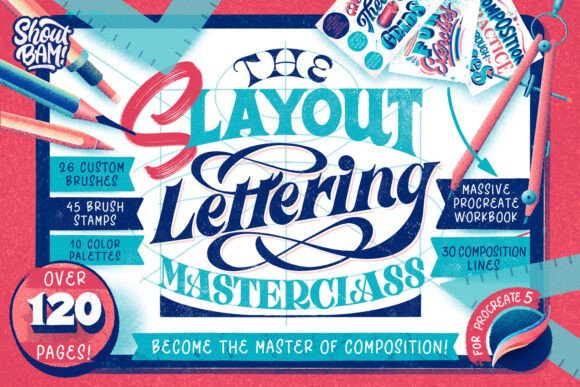
The Slayout Lettering Masterclass
The Slayout Lettering Masterclass์™€ ๊ฐ™์€ ๊ณ ํ’ˆ์งˆ ์ž์‚ฐ์„ ์ฐพ๊ณ  ์žˆ๋‹ค๋ฉด ์ด ํ”„๋ฆฌ๋ฏธ์—„ ํŒจํ‚ค์ง€๋Š” ์ฐฝ์˜์ ์ธ ํ”„๋กœ์ ํŠธ๋ฅผ ์œ„ํ•œ ํ™˜์ƒ์ ์ธ ์„ ํƒ์ž…๋‹ˆ๋‹ค.
์ •๋ฐ€ํ•˜๊ฒŒ ์ œ์ž‘๋œ The Slayout Lettering Masterclass๋Š” ๊น”๋”ํ•œ ๋ฒกํ„ฐ, ๋ถ€๋“œ๋Ÿฌ์šด ํƒ€์ดํฌ๊ทธ๋ž˜ํ”ผ ๋ฐ ์•ˆ์‹ฌํ•  ์ˆ˜ ์žˆ๋Š” ์ƒ์—…์šฉ ๋ผ์ด์„ ์Šค๋ฅผ ์ œ๊ณตํ•ฉ๋‹ˆ๋‹ค.
POD(์ฃผ๋ฌธํ˜• ์ธ์‡„) ์ œํ’ˆ, ๊ฒฐํ˜ผ์‹ ์ดˆ๋Œ€์žฅ ๋˜๋Š” ์†Œ์…œ ๋ฏธ๋””์–ด ๊ทธ๋ž˜ํ”ฝ์„ ๋งŒ๋“ค ๋•Œ The Slayout Lettering Masterclass๋Š” ์ด์ƒ์ ์ธ ์„ ํƒ์ž…๋‹ˆ๋‹ค.